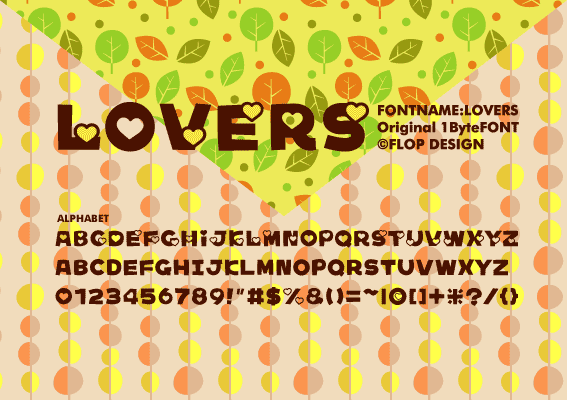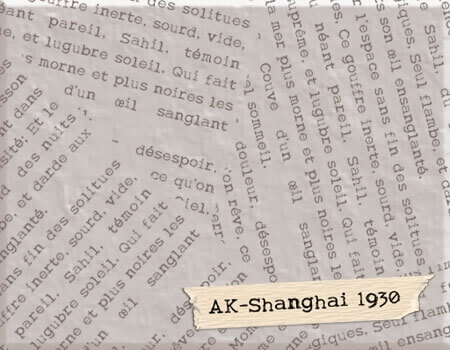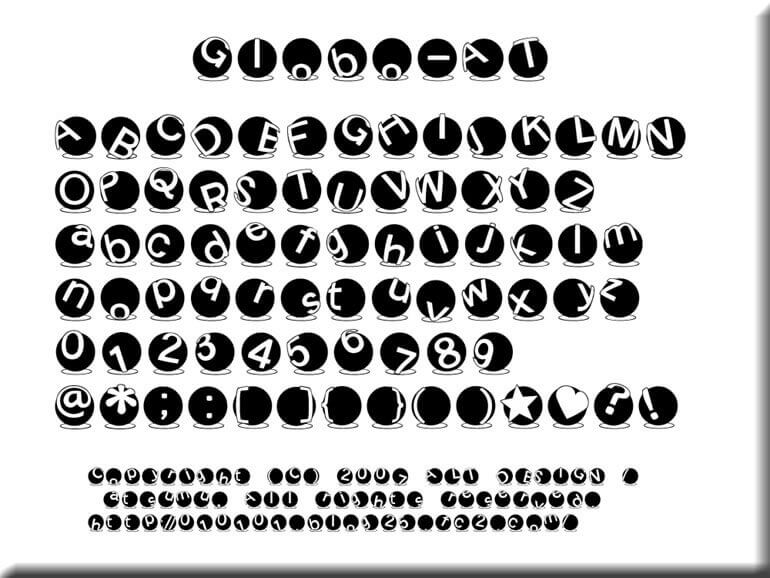
ハートがついてる可愛いフォント7つ
女性らしいデザインにピッタリなハートフォントを7つまとめました。アイコンとして使ったりデザインの一部に使ったりと便利なフォントになっています。バレンタインなどのイベントに大活躍間違いなし!
AK-ANGEL
天使の羽がついているかわいいフォント。小文字で打つとそのまま、大文字で打つと陰付きになります。
AK-My Prince
つながった筆記体を表現したフォント。大文字と数字は文字の最後がクルッとしています。
AK-Shanghai1930
タイプライター風フォント。フランス語とドイツ語に対応しています。
Emoji Font
絵文字のみが収録されているフォント。ビットマップフォントです。
Globo-AT
立体的な球体に文字が貼られているコミカルなフォント。
Heart Full
いろいろな種類のハートが収録されているフォント。
ラバーズフォント
文字の中にハートがデザインされたフォント。